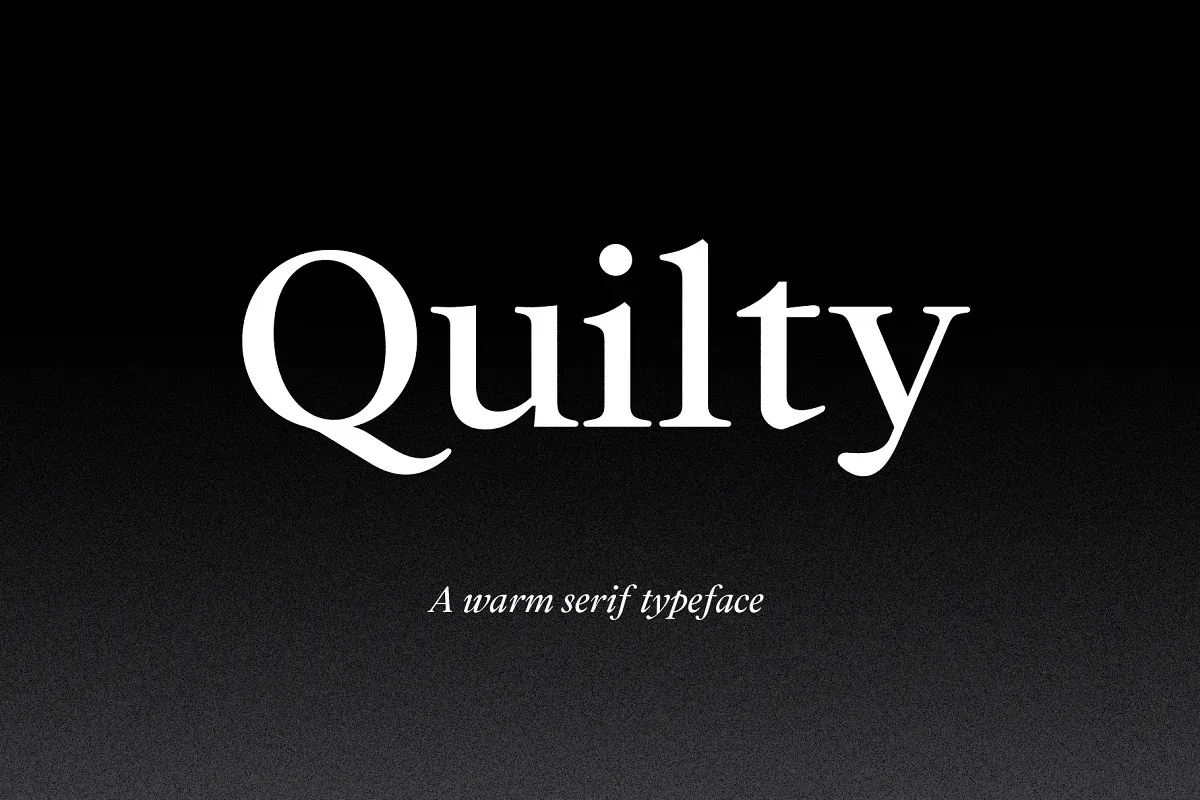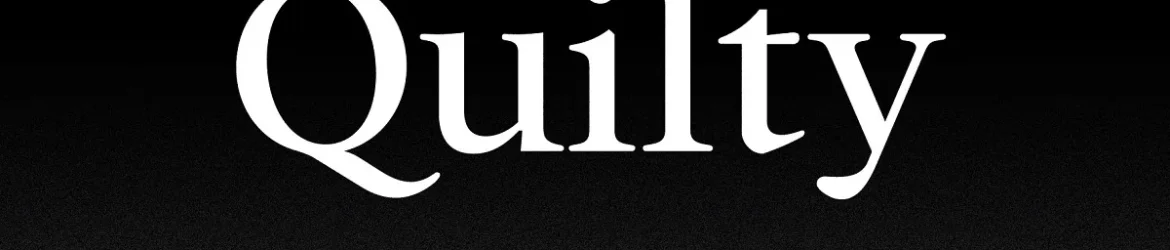
A Quilty Font é uma nova família geométrica de tipo serif que traz uma aparência moderna para qualquer projeto. Foi cuidadosamente projetada para ser a escolha perfeita para um tipo serif, oferecendo um visual sólido e forte em ambientes com grande quantidade de texto. Ela também atinge excelentes resultados como fonte de destaque. Quilty é uma excelente adição à sua coleção de fontes, especialmente útil em design tipográfico complexo ou sites que exigem uma aparência tradicional e elegante sem perder o toque moderno. Se você está procurando por uma fonte serif com um visual leve e moderno, essa pode ser a solução perfeita.